Akhir-akhir pembicaraan tentang olahraga dalam media sosial meningkatkan berkat diadakannya olimpik, mengikuti pembicaraan menggunakan desain yang relevan akan meningkatkan engagement. Berbicara soal desain bertema sport, penggunaan elemen visualnya juga harus relevan untuk setiap lini olahraga. Setiap desain tema sport bisa memiliki rekomendasi gaya font berbeda menyesuaikan jenis sport yang dibahas agar relevan.
Elemen visual seperti font dapat menciptakan kesan tertentu dalam desain grafis. Setiap cabang olahraga memiliki citra dan kesan yang berbeda pula, yang mana membutuhkan elemen yang berbeda. Gunakan jenis font berbeda untuk setiap cabang olahraga agar desain visual tampil menarik dan relevan.
Sebelum itu pahami pula ciri umum desain bertema sport serta elemen visual yang kerap digunakan dalam desain sport. Penggunaan elemen visual yang tepat akan menciptakan desain yang relevan dan menarik.
ELEMEN VISUAL KHAS SETIAP CABANG OLAHRAGA
Desain bertema olahraga secara menggunakan gaya desain yang tampil kuat, tajam dan menunjukkan semangat olahraga. Penggunaan elemen visual untuk merepresentasikan setiap cabang olahraga akan berbeda. Simak beberapa elemen visual yang khas setiap tema desain sport:
Sepak Bola yang Bergaya Strong dan Powerful
Meski secara umum desain poster sport bertema strong dan kuat, ada beberapa cabang olahraga yang tampil beda. Olahraga sepak bola misalnya akan memiliki desain poster yang menyoroti bola. Ikon gambar bola baik ilustrasi maupun gambar akan ditonjolkan untuk memudahkan audiens memahami pesan yang disampaikan.
Selain pola desain poster olahraga soccer ini juga sering menggunakan gambar siluet pemain yang sedang menendang untuk mencerminkan olahraga ini dengan baik. Sementara untuk warnanya desain poster olahraga soccer akan menggunakan warna hijau yang dominan. Warna hijau mencerminkan warna lapangan bola, terkadang juga dikombinasikan dengan warna biru agar harmonis.
Gymnastics dengan Gaya Desain Elegan
Berbeda dengan desain untuk olahraga soccer yang tampil kuat, tema desain gymnastic seringkali menggunakan tema desain yang elegan. Poster untuk jenis sport ini biasanya memiliki penggunaan gambar visual alat gymnastic seperti pita, bola, atau hula hoop. Untuk mencerminkan gymnastics dengan baik, gunakan juga ilustrasi seperti pose senam ritmik yang indah dan elegan. Untuk mendukung tampilan yang elegan penggunaan warna-warna pastel, warna cerah dan gradasi yang menarik akan relevan dengan gymnastic.
Tennis dengan Gaya Sporty
Penggunaan desain grafis bertema olahraga tenis biasanya identik dengan warna hijau dan kuning. Kedua warna ini merupakan lapangan tenis dan warna bola tenis, warna ini akan efektif untuk menciptakan kesan desain yang sporty. Untuk merepresentasikan desain bertema tenis dengan baik, gunakan juga gambar raket tenis dan net tenis. Terkadang desain akan menggunakan latar belakang berupa lapangan tenis serta ilustrasi siluet orang bermain tenis agar semakin menarik.
Poster Renang yang Fresh
Untuk desain poster olahraga untuk renang biasanya memiliki warna dominan biru untuk merepresentasikan kolam renang dan menciptakan kesan menyegarkan. Penggunaan warna biru akan relevan jika ditambahkan pula gambar atau ilustrasi orang yang sedang berenang. Ilustrasi atau gambar kolam akan menjadi fokus utama dalam desain poster sport untuk renang.
Volleyball yang Strong dan Kerjasama
Tema poster tentang olahraga bola voli bisa menggunakan ilustrasi bola yang memiliki garis coretan berbeda dengan bola soccer. Gunakan gambar dan ilustrasi boola voli untuk mencerminkan canang olahraga dengan baik. Selain itu terkadang siluet atlet sedang memukul bola voli akan efektif. Untuk warna yang digunakan dalam poster tema olahraga ini mengambil warna bola putih kombinasi biru dan kuning,
REKOMENDASI FONT SPORT UNTUK SETIAP CABANG OLAHRAGA
Untuk membuat desain poster bertema olahraga semakin menarik dan merepresentasikan setiap cabang olahraga dengan baik. Gunakan gaya font yang memiliki bentuk huruf yang mencerminkan jenis caang sport agar memiliki tampilan desain yang relevan. Berikut beberapa rekomendasi font untuk setiap canang sport:
Monoline untuk Gymnastics
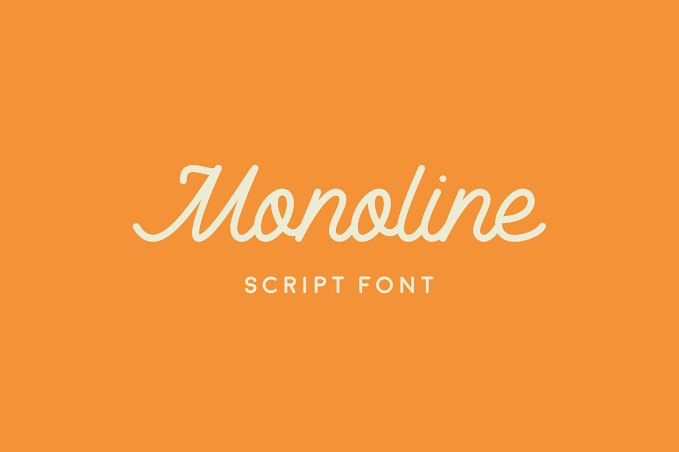
Gaya font ini memiliki tampilan font script lain sederhana, huruf-huruf dalam jenis font ini saling bersambung dan menciptakan tampilan elegan. Meski bersambung garis-garis font bulat tidak lancip dan elegan, hal ini membuat teks dalam desain bukan elegan melainkan klasik. Gaya script dalam fnt menciptakan kesan klasik dan elegan sehingga cocok untuk desain sport gymnastic.
Penggunaan font latin untuk olahraga gymnastic akan tampil elegan dan indah cocok dengan pose olahraga gymnastic yang indah. Pose siluet dari olahraga ini yang tampil indah akan cocok dengan penggunaan font yang elegan. Font ini masih memiliki keterbacaan yang baik untuk digunakan dalam desain poster sebagai headline.
Rugrats Sans untuk Soccer
Untuk desain olahraga soccer gunakan jenis font bersih yang mudah dibaca seperti font sans serif, penggunaan font rugrat sans yang bersih ini akan memudahkan teks desain terbaca. Gaya font yang bersih akan efektif untuk mencerminkan desain strong dan bersemangat. Untuk kebutuhan poster sepak bola gunakan font ini dalam ukuran yang besar dengan gaya huruf yang tebal.
Tampilan font yang bersih cocok dengan citra olahraga sepak bola, font ini tidak hanya mudah dibaca tetapi mencerminkan kesan olahraga yang bersemangat. Gunakan font ini untuk font judul ataupun teks berukuran kecil pada desain poster. Untuk ukuran kecil sekalipun, font ini akan mudah untuk dibaca sehingga efektif dan relevan dengan citra soccer.
Baca juga: Inspirasi Font untuk Branding Vintage Bisnis Kecil
Perandory untuk Tennis
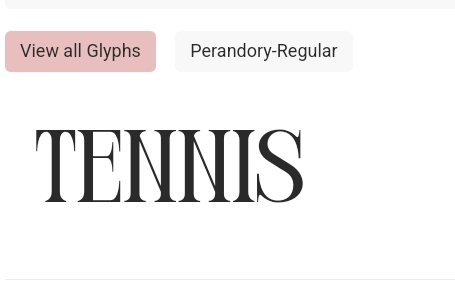
Desain poster untuk event pertandingan tenis biasanya identik dengan warna hijau dan kuning sehingga tampil fresh dan sporty. Gaya desain yang fresh untuk mencerminkan olahraga tenis juga efektif menggunakan gaya font yang menarik. Penggunaan gaya font serif seperti font perandory juga cocok untuk desain olahraga tenis karena mencerminkan kesan stylish dan sporty.
Font serif yang tampil kapital ini cocok untuk digunakan sebagai font judul, meski tampil tinggi dan sedikit rapat, font tetap mudah untuk dibaca. Penggunaan font serif ini bisa menciptakan tema desain yang terlihat elegan dan formal. Agar mudah terbaca, hindari menggunakan jenis font ini dalam ukuran kecil pada poster tenis.
Sugar Pie untuk Swimming
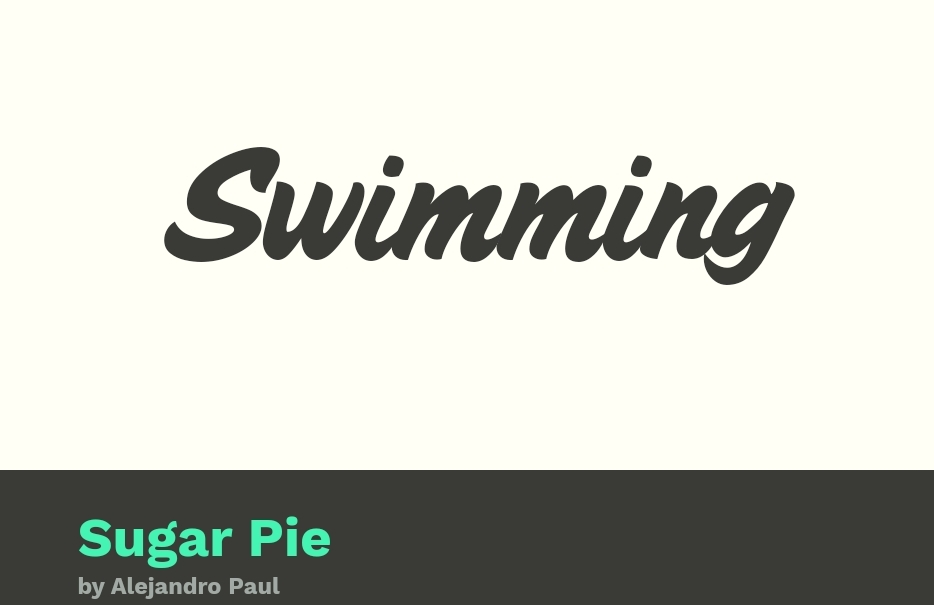
Kebanyakan gaya font yang digunakan dalam desain grafis bertema sport adalah font tebal agar menciptakan kesan bersemangat dan sporty. Jenis font ini memiliki gaya huruf script yang tebal dan mudah untuk dibaca jika berukuran besar. Font tebal ini sebaiknya digunakan dalam desain grafis bertema sport yang ingin menunjukkan kesan energik dan semangat.
Desain poster dengan judul yang menggunakan font tebal seperti font sugar pie ini akan lebih mudah untuk dibaca. Gunakan hanya untuk font judul atau headline agar teks mudah dibaca. Gaya huruf yang mengikuti tulisan tangan ini terlihat alami sehingga efektif untuk menciptakan desain poster yang ramah dan menyenangkan sesuai citra olahraga renang.
Baca juga: 5 Kombinasi Font untuk Desain Elegan dan Mewah
Della Robbia untuk Golf
Untuk poster yang digunakan dalam desain olahraga golf biasanya akan golf bukanlah olahraga gelap. Olahraga ini seringkali dikaitkan dengan sport untuk orang kaya dengan penggunaan seragam yang elegan. Sehingga pada poster untuk golf ini sebaiknya menggunakan jenis font serif yang elegan dan berkesan mewah.
Gaya font serif ini akan mempresentasikan citra olahraga golf dengan baik, font serif yang elegan akan tampil menawan. Font ini memiliki tampilan bersih sehingga mudah terbaca bahkan jika digunakan dalam ukuran yang kecil. Gunakan font serif ini untuk font judul pada poster golf agar menciptakan visual yang elegan dan stylish.
Monument Untuk Track and Field
Dalam desain poster olahraga track dan field ini akan relevan jika menggunakan gaya font yang tampil strong dan tegas. Hal ini karena jenis font tegas dan tajam akan merepresentasikan kesan olahraga yang kuat. Font monument ini bisa digunakan dalam versi font yang tebal agar tampil kuat dan tajam.
Untuk font judul, desain poster akan tampil strong dan menunjukkan jika ini adalah olahraga yang membutuhkan banyak kekuatan. Font ini memiliki tampilan huruf yang bersih sehingga mudah dibaca meski digunakan dalam vers tipis dan berukuran kecil.
Fineday Connect untuk Volleyball
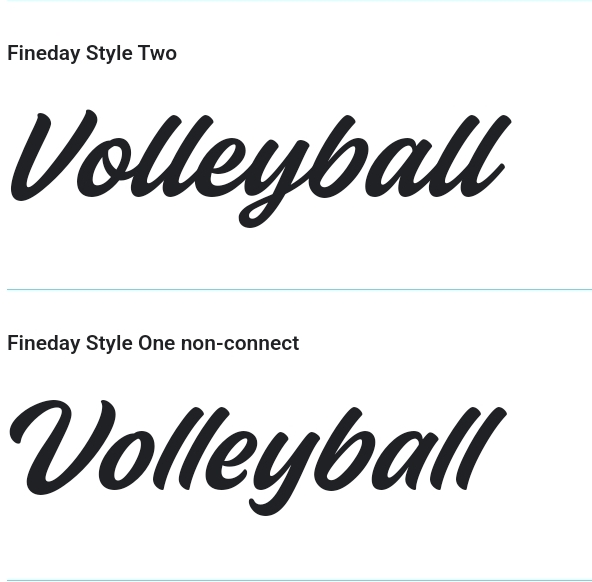
Desain poster untuk olahraga volleyball juga akan cocok menggunakan jenis font tebal yang bersih dan mudah dibaca. Font judul yang tebal akan efektif untuk dibaca terutama jika digunakan sebagai font judul dan headline. Selain menggunakan jenis font tajam dan kaku, font script yang bersih juga cocok untuk desain olahraga bola voli.
Untuk menciptakan desain bertema sport yang relevan dan bisa mencerminkan setiap cabang olahraga. Desain bertema olahraga umumnya akan memiliki gaya font yang tebal, kaku, dan menyenangkan. Gaya font yang relevan dengan citra setiap cabang sport akan tampil menarik dan relevan, beberapa rekomendasi font tersebut dipilih berdasarkan cabang olahrga agar lebih efektif.